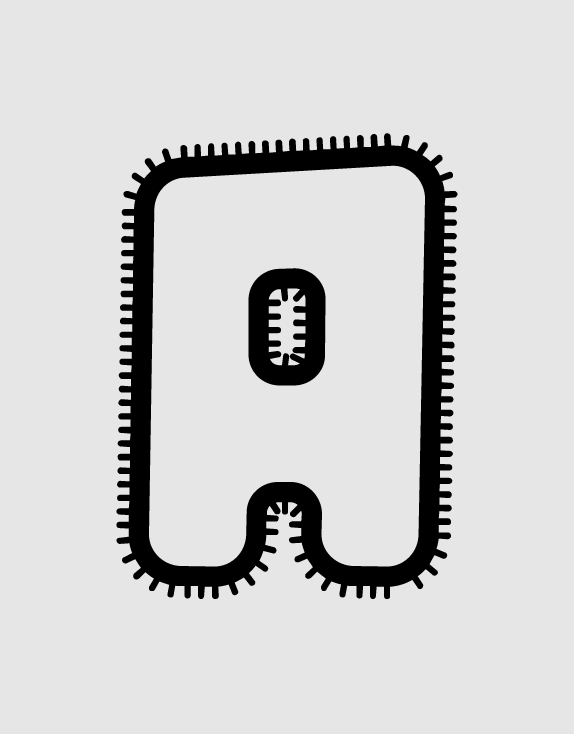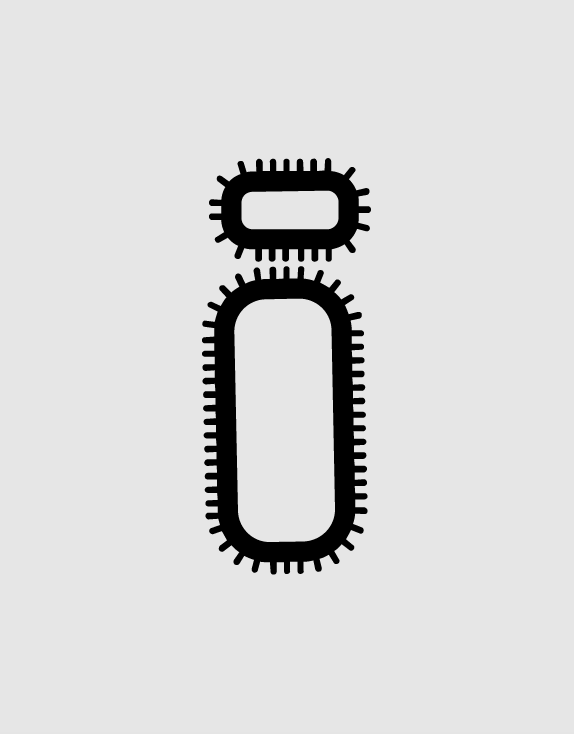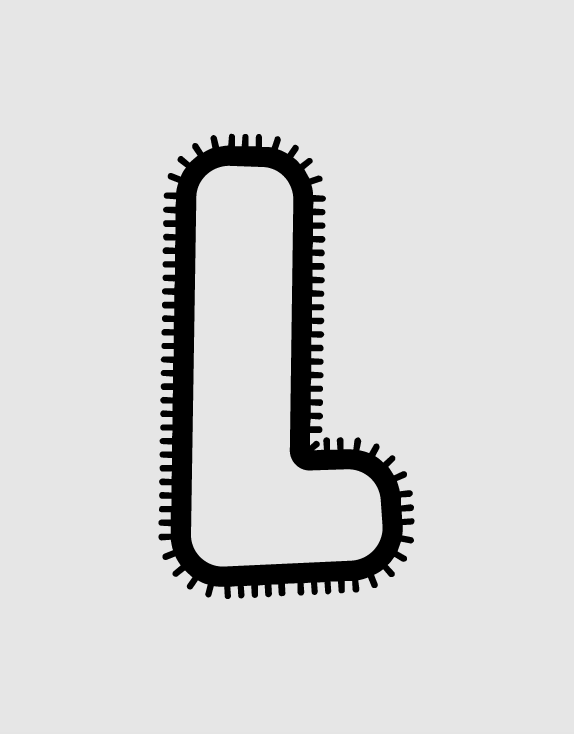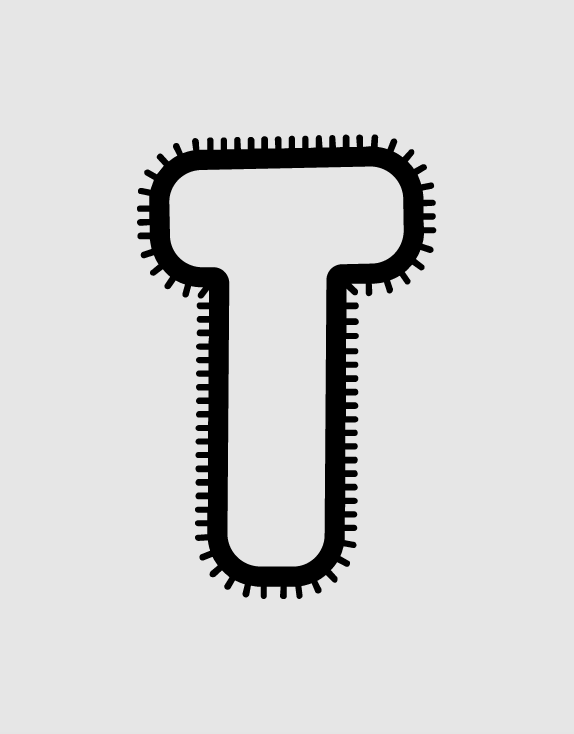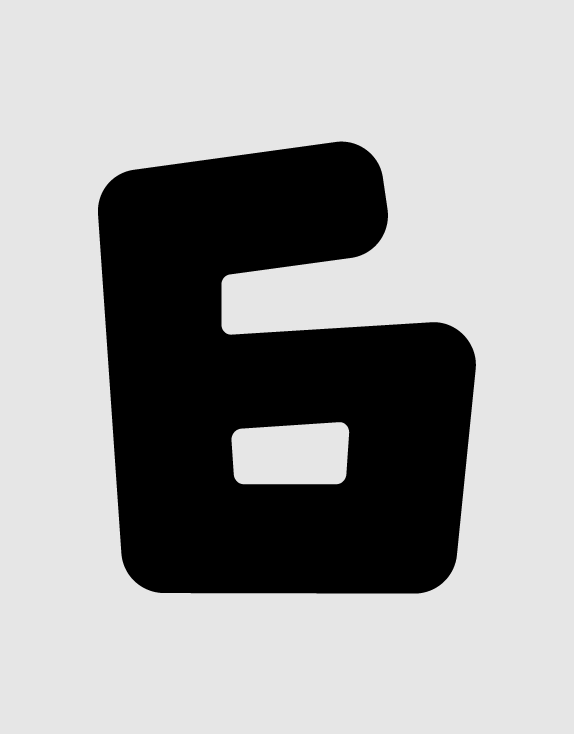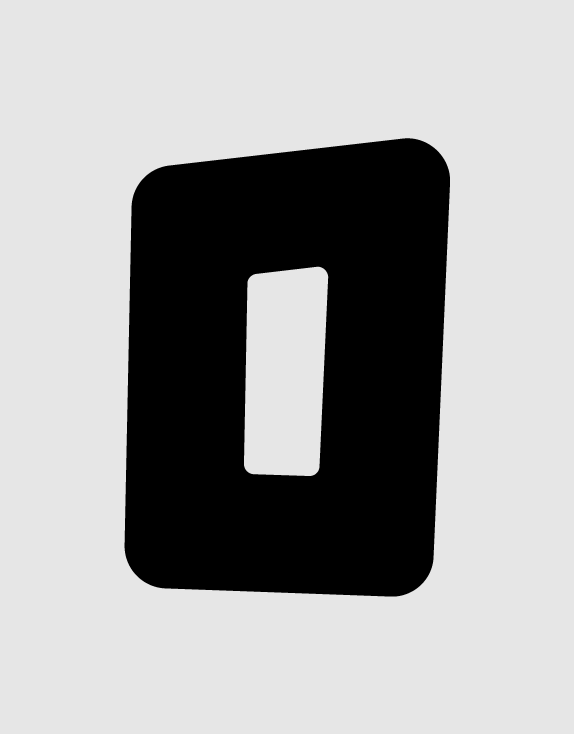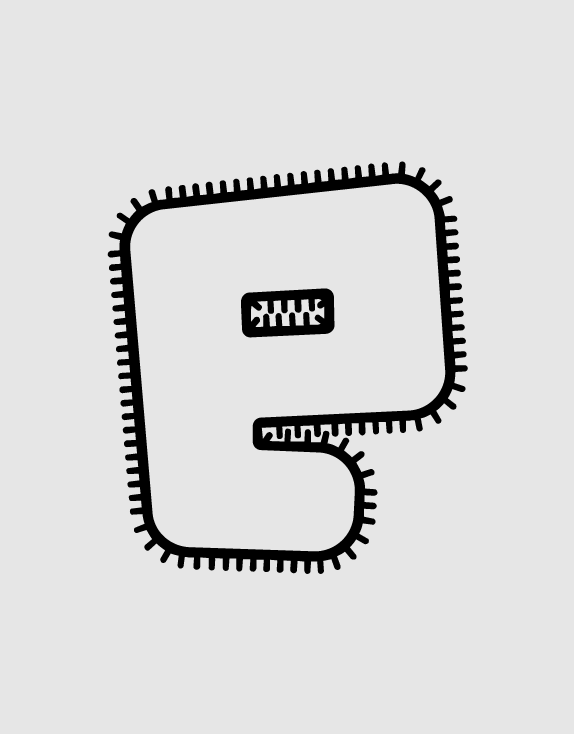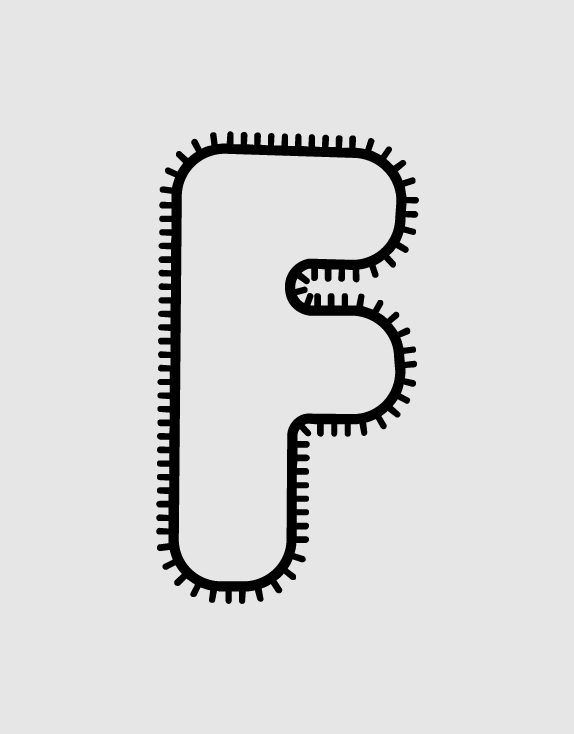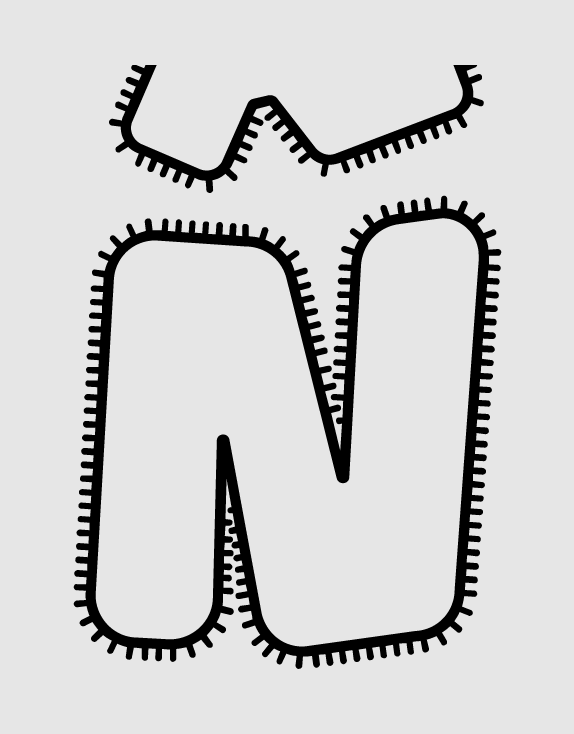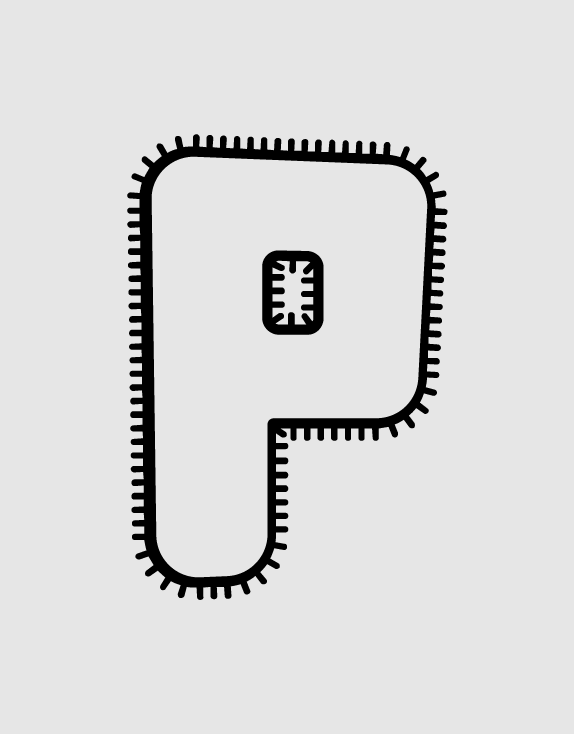
6 tipografías combinables para jugar con títulos | Display font
d puntillas por la tipografía
Después de un trimestre muy ocupado, por fin, he cogido una semana de tiempo libre para dibujar estas 6  fuentes tipográficas, proyecto que tenía pendiente hace tiempo.
Propuesta para logotipo de tienda de moda artesanal.La idea del desarrollo de esta tipografía veraniega surge de una propuesta, no elegida, para un logotipo de una cadena de tiendas llamada “cactus”. En aquel momento dibujé las 6 letras del nombre, y a partir del diseño original he creado el resto del alfabeto que hoy os presento. La tipografía dispone de 377 glifos y es válida para cualquier alfabeto derivado del latín.
Esta colección de fuentes es apropiada para uso en carteles y posters tipográficos o vectoriales, siempre que el estilo de ilustración, inherente de la tipografía, este acorde a lo que buscas.
Combinando d puntillas
La familia tipográfica “d puntillas” es un conjunto de 6 fuentes display combinables para la creación de títulos policromados.
Cartel tipográfico: d puntillas: a set of 6 combinable typefaces.La técnica consiste en clonar las capas de texto y combinando las fuentes conseguirás títulos puramente tipográficos a dos o tres colores (policromos), para ello debemos instalar las 6 tipografías y jugar con las combinaciones, en el poster de la izquierda te sugiero algunas. Usa tu programa de diseño favorito (Freehand, Illustrator, Corel, Photoshop, etc) para probar estas tipografías.
d puntillas por el nombre
La idea de desarrollar un conjunto de tipografías combinables me condujo a encontrar un nombre, donde, combinables también han sido los siguientes 3 conceptos por los cuales he nominado a esta familia de fuentes:
• Pasar d puntillas (to tiptoe): Tratar algo de pasada, sin profundizar ni insistir en ello.(DUE)… porque es un diseño tipográfico experimental.
• Puntillas [a] (Lace): Encaje generalmente estrecho que forma ondas o picos en una de sus orillas y que se pone como adorno en el borde de pañuelos, toallas, vestidos, etc.(RAE)… me recuerdan a las puntillas de las ropas de bebe.
• Puntillas de calamar (Tiptoes squid): Caprichosos calamares de tamaño diminuto, lo ideal es tomarlos fritos con una cervecita, echando humo, a la orilla del mar un verano cualquiera…
d puntillas, a set of 6 combinable typefaces